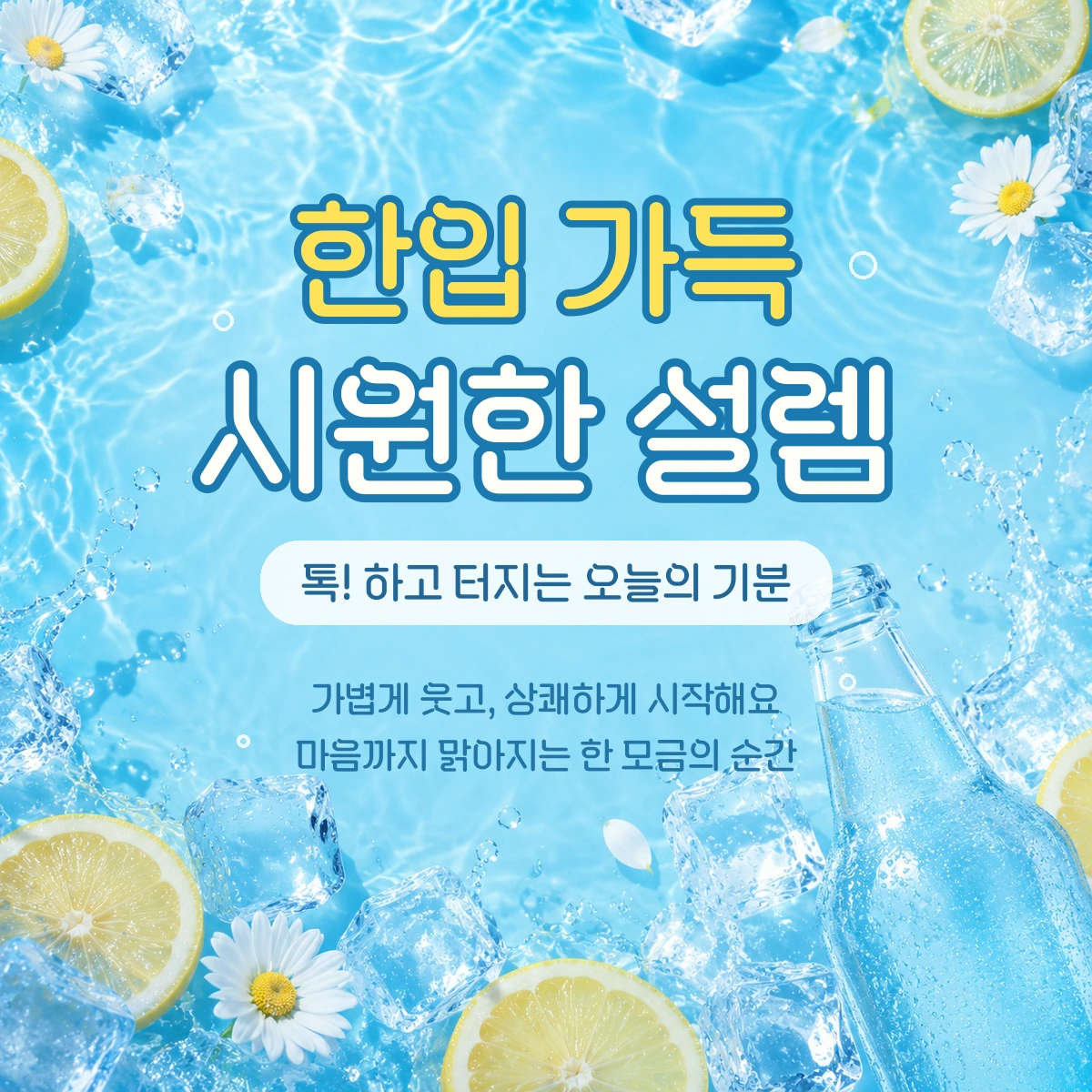
시원한 설레임체 무료폰트
시원한 설레임체 — 롯데제과에서 배포하는 무료 폰트입니다. 둥글고 부드러운 형태로 설레임의 상쾌하고 발랄한 이미지를 담은 장식체
롯데제과가 2003년에 출시해 오래 사랑받아 온 밀크쉐이크 아이스크림 설레임을 서체로 옮긴 글꼴입니다. 제품 패키지를 새로 단장하면서 그에 맞춰 함께 개발했다고 밝히고 있습니다.
제작사가 설명하는 조형은 로고에서 출발합니다. 설레임 로고의 ㅅ과 ㅇ 형태를 모티브로 유지하되 쓰기 편하도록 형태의 균형을 조절했고, 밀키한 형태의 글자 모양에 제품이 떠오르는 포인트 요소를 넣어 밀크쉐이크 아이스크림을 연상시키도록 했다는 것입니다. 유연한 곡선을 살리면서 가독성도 함께 챙겼다고 덧붙입니다.